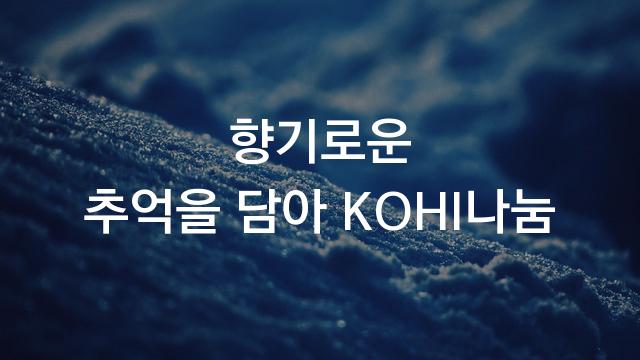
KOHI배움은 한국보건복지인력개발원에서 제작한 제목용 폰트로, 꽉 찬 고딕 스타일을 자랑합니다. 이 폰트는 뚜렷한 가독성과 강한 인상을 주며, 각 문자의 채워진 공간이 시각적 안정감을 제공합니다.
KOHI배움은(는)
기본 고딕, 굵은 고딕, 단단함, 길고/크고 계열의 생김새를 가지고 있으며
교육 자료, 프레젠테이션, 보고서/문서 등에서 자주 활용되며, 효과적인 메시지 전달에 적합합니다.
이 폰트는 교육, 출판/미디어, 라이프스타일 분야에 잘 어울리며,
친근한, 명확한, 편안한 느낌을 담고 있는 것이 특징입니다.